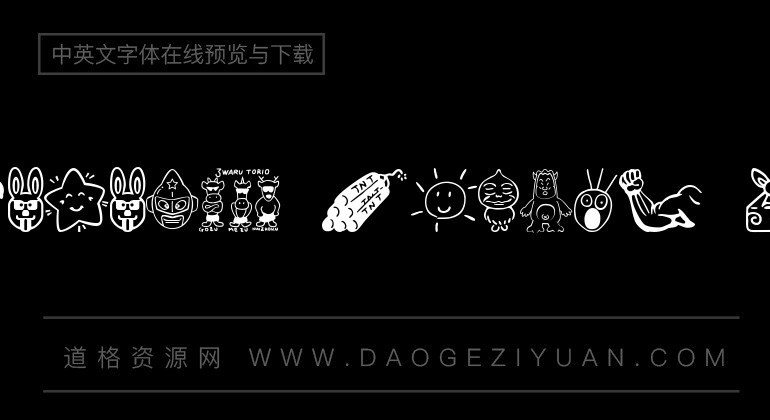
Sakabe Things 01 是一款可爱的日式涂鸦字体,由日本设计师Sakabe创作。它具有温暖而可爱的气息,可以用于各种形式的文字排版,从标题、小标题到正文,都可以使用。它的特点是简约而不失可爱,极具视觉冲击力,可以提高文字的阅读体验。它也可以用于宣传单、海报、T恤等各种印刷品的设计,使它们更具有视觉冲击力。内容介绍
Sakabe Things 01是一款非常不错的手写艺术字体,具有很好的视觉感,适合于文化类的宣传设计、商业类品牌的广告和产品包装设计以及个性化文字排版等较多场景。